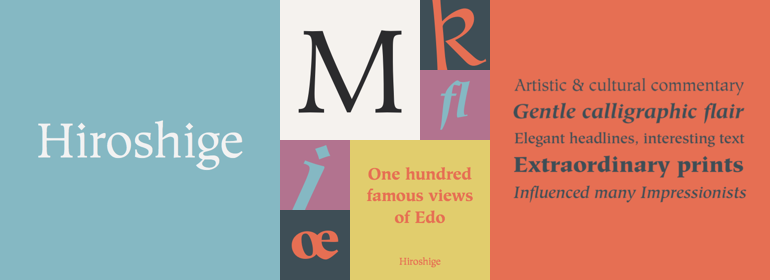
Hiroshige™
Hiroshige™,这款字体结构工整、笔画清晰,兼顾美观与易读性,适用于标题、正文、海报、包装、LOGO 等多种场景。字形优雅稳定,风格百搭耐看,适配日常排版与创意设计,让文字呈现更舒适、更具质感。Hiroshige™一笔一画,皆是细节,以均衡的比例、流畅的线条打造舒适视觉体验,字形端正大气,风格简约现代。无论是商业设计、品牌宣传还是日常排版,都能轻松驾驭,让文字更有格调与力量。Hiroshige™字体下载。
字体品牌: Monotype 设计师:Batty,Cynthia Hollandsworth 字体分类:衬线体 字体属性:外文 字符集:Unicode 发布时间: 2018